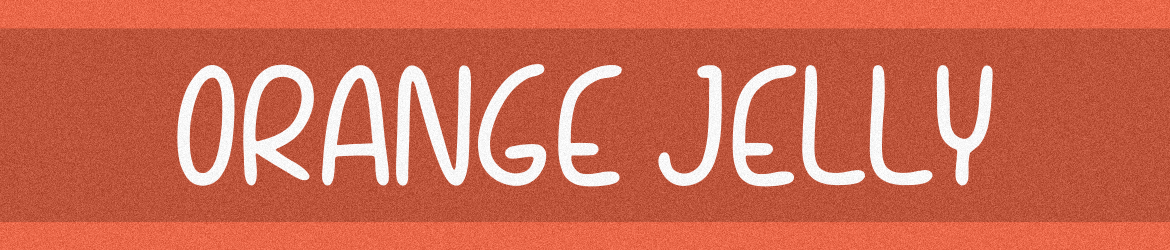
Esta fonte ‘Orange Jelly Font’ é uma criatura encantadora e descontraída, perfeitamente projetada para aqueles que valorizam a mão-de-viva no design. Ideal tanto para assinaturas quanto para textos informativos, esta font será um tesouro valioso para seu acervo de fontes. Seja você designer de gráficos ou web, sua produção ganhará vida e personalidade com o ‘Orange Jelly Font’. Com uma caligrafia desenfreada e amigável, não importa qual seja o tópico ou a mensagem que pretende transmitir, esta font garantirá um toque único em seu trabalho. Enigma Lettering Studio criou este design de fonte, oferecendo aos designers do mundo todo uma maneira divertida e criativa de dar vida às suas criações. Este não é apenas mais uma opção na sua biblioteca de fontes – ele é o detalhe que pode fazer a diferença. Em um ambiente digital cheio de textos formais, esta font traz um toque suave e descontraído, tornando-a perfeita para assinaturas ou qualquer outro uso que você possa imaginar. Adquira ‘Orange Jelly Font’ hoje e revolucione o design do seu trabalho!